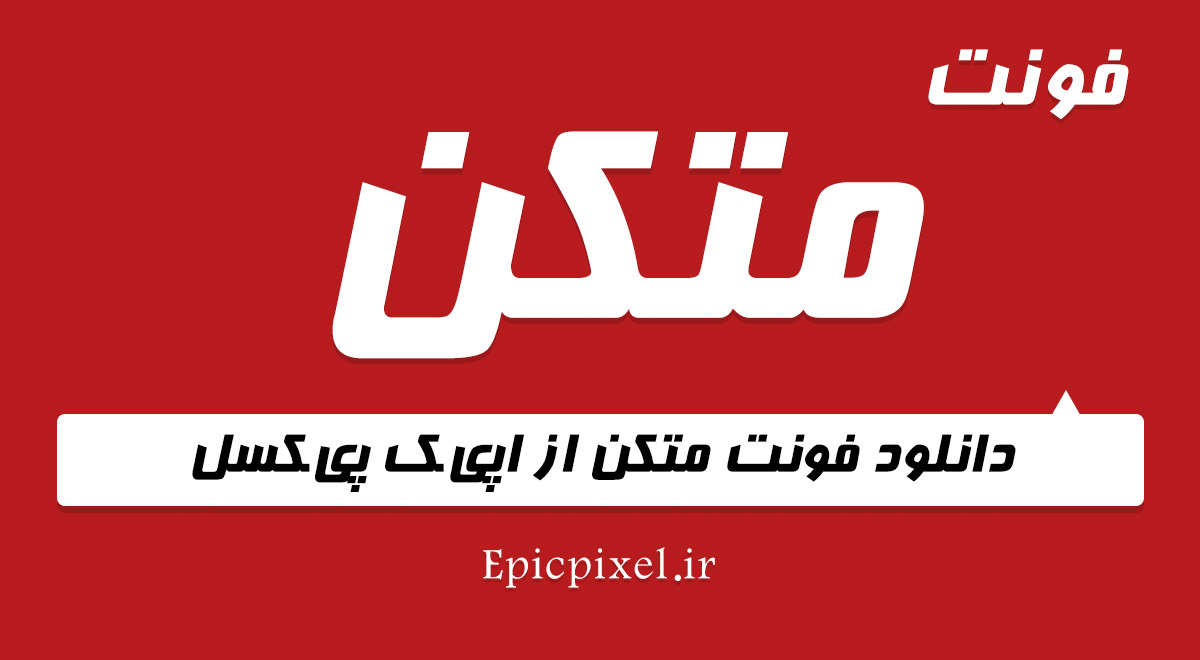
18 فونت متکن عربی
فونت متکن عربی از ویژگی های بارزی برخوردار است که آن را به انتخابی هوشمندانه برای طراحی های شما تبدیل می کند. این فونت با ساختار هندسی منحصر به فرد و خوانایی بالا، هم در متون بلند و هم کوتاه قابل استفاده است. طراحی مینیمال و مدرن آن باعث می شود تا به راحتی با سایر عناصر گرافیکی و متن های دیگر هماهنگ شود.
نکته ی مثبت دیگر این فونت، پشتیبانی از حروف خاص و علائم نگارشی عربی است که باعث می شود متون شما از هر لحاظ کامل و بی نقص باشند. این ویژگی به طراحان امکان می دهد تا بدون نگرانی از نبود حروف خاص، از این فونت در پروژه های مختلف استفاده کنند.
در کنار مزایای فراوان، ممکن است عدم وجود نسخه های مختلف برای استفاده در عناوین و متن های عادی، یک نقطه ضعف به حساب بیاید. اما با توجه به رایگان بودن این فونت و قابلیت های گسترده ی آن، این نکته کمتر به چشم می آید.
اگر به دنبال فونتی هستید که علاوه بر زیبایی و سادگی، عملکرد بی نقصی داشته باشد، فونت موتکن عربی می تواند گزینه ی ایده آلی برای شما باشد. علاوه بر این، رایگان بودن آن نیز از دیگر مزایای بزرگ این فونت است که آن را برای همه ی طراحان دست یافتنی می کند.